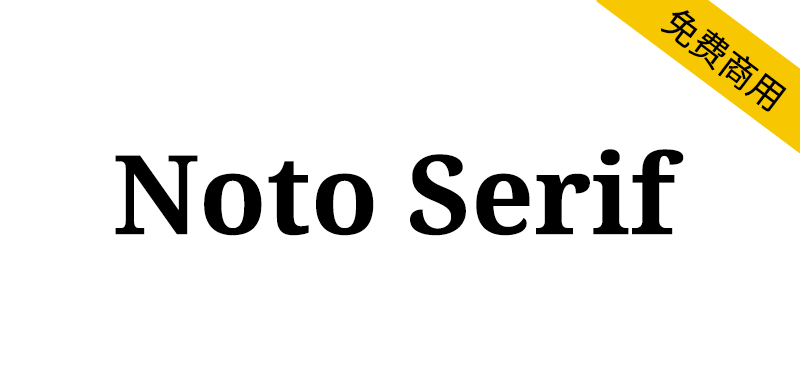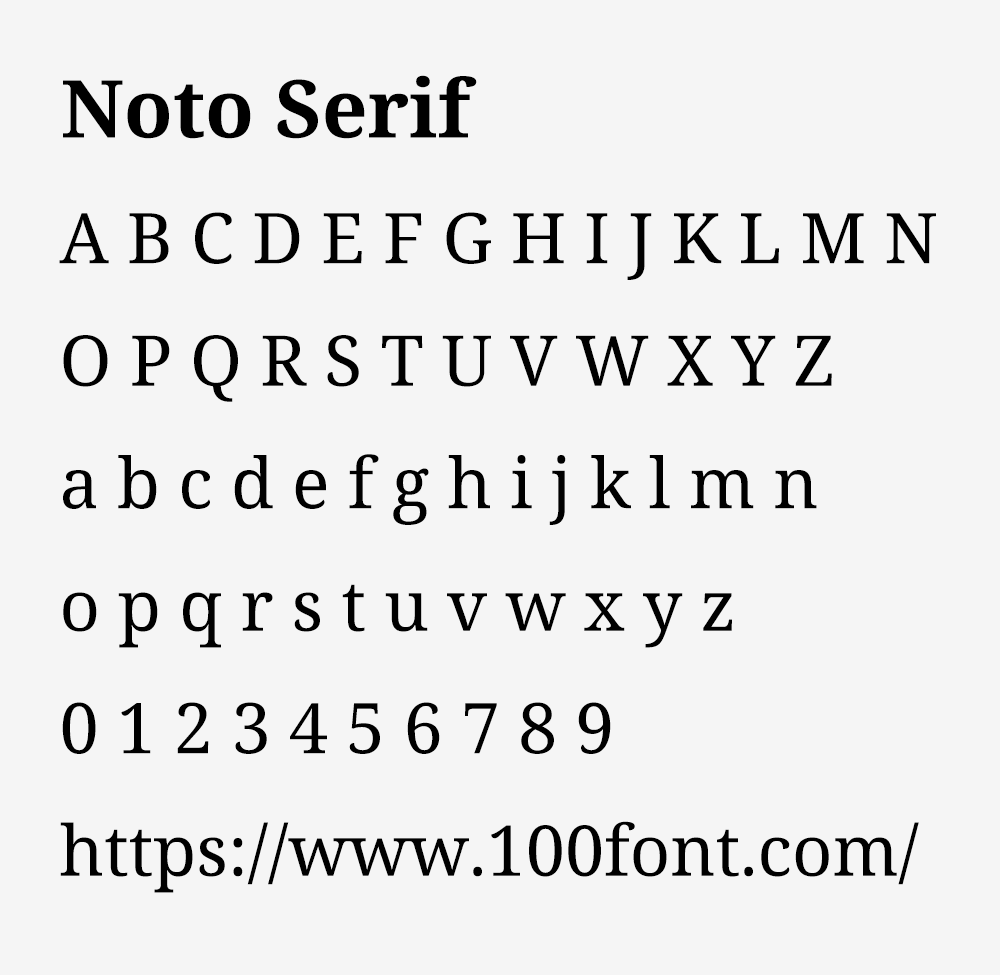
Noto是一套高质量字体合集,涵盖无衬线体、衬线体、等宽体等多种字重和宽度的字体,支持超过1000种语言及150种以上的书写系统。(Noto is a collection of high-quality fonts with multiple weights and widths in sans, serif, mono, and other styles, in more than 1,000 languages and over 150 writing systems.)